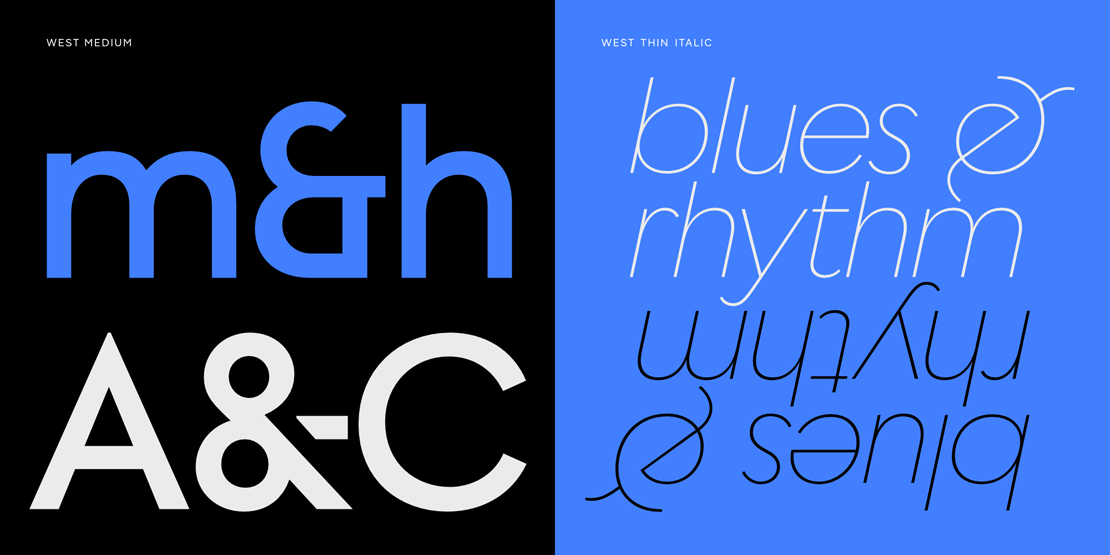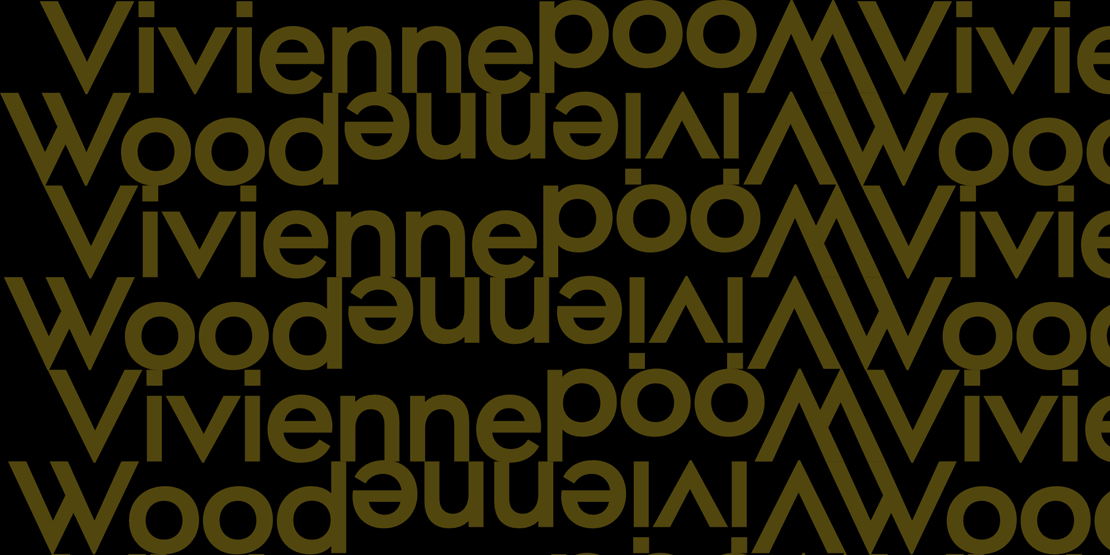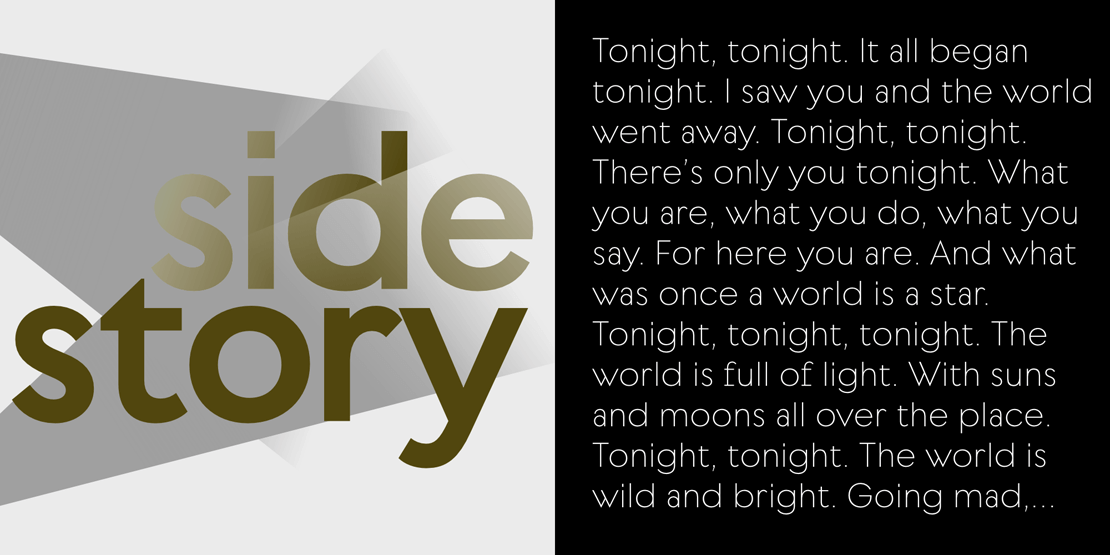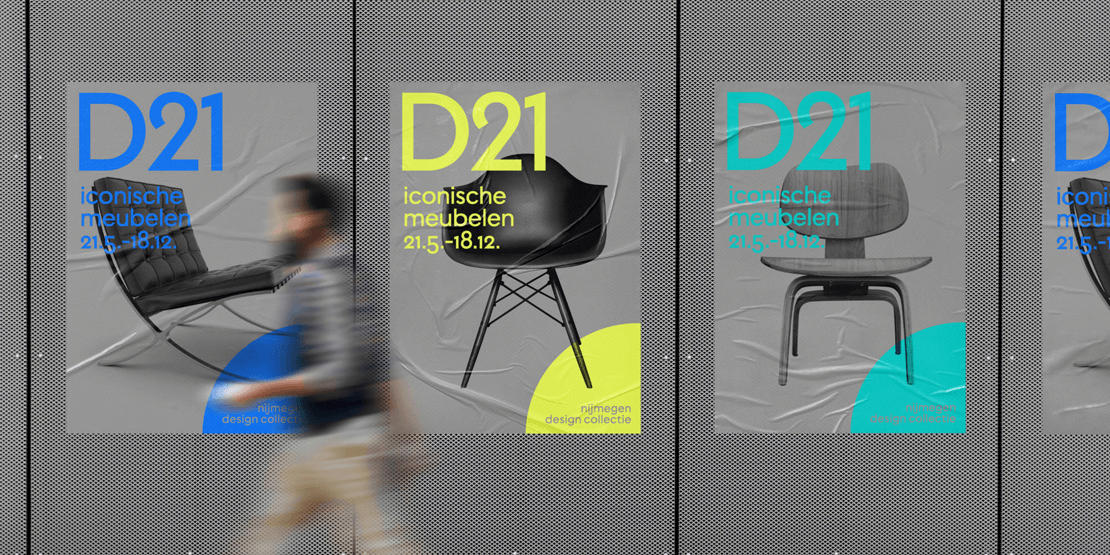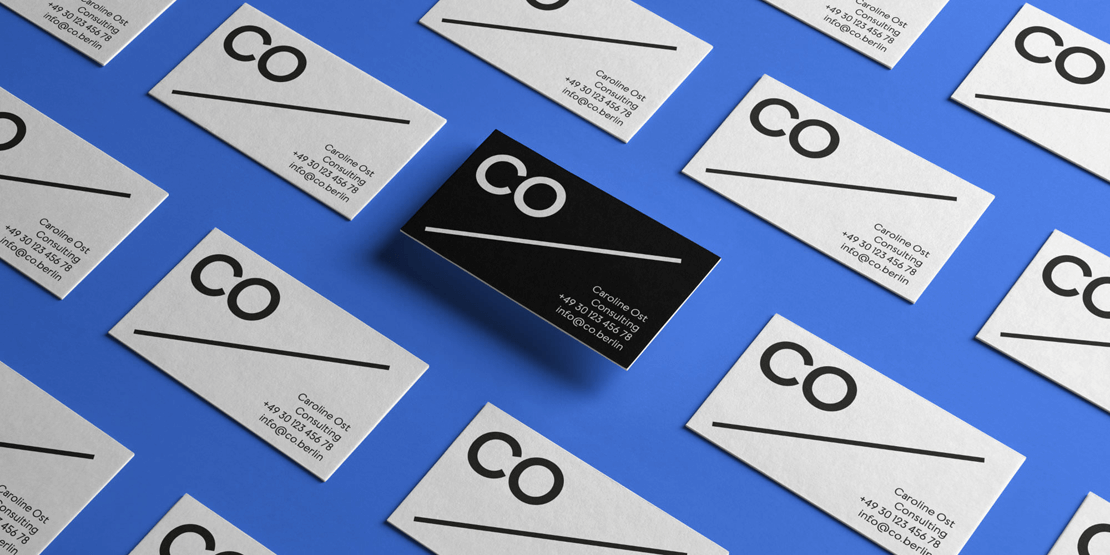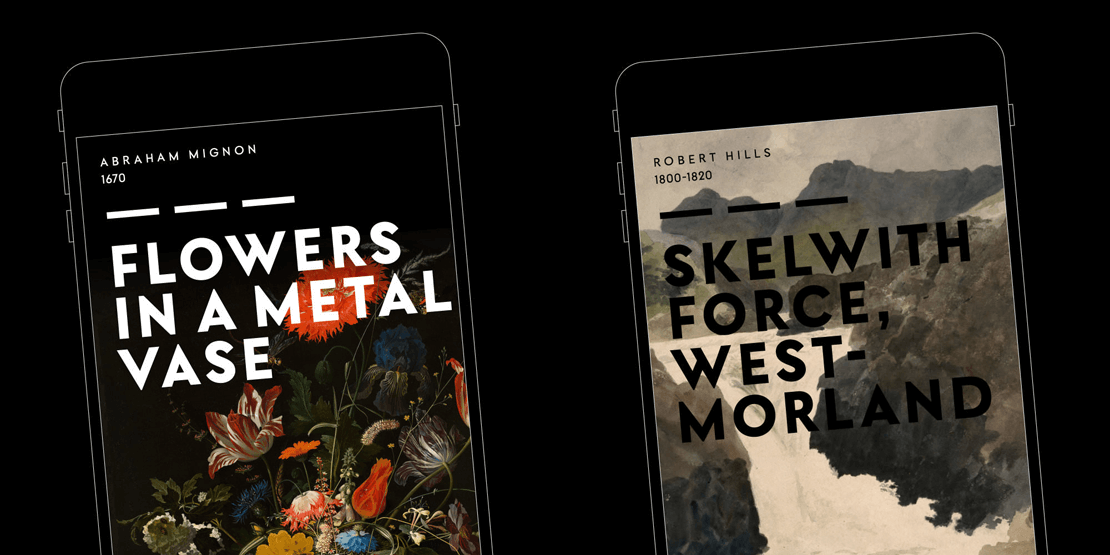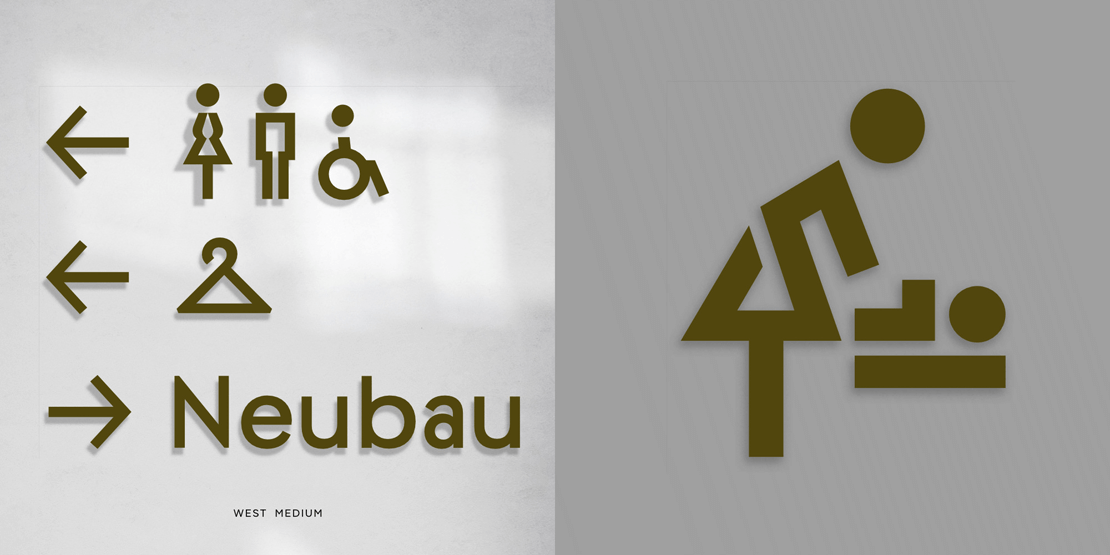
West: Geometrische Serifenlose mit eigenständigem Charakter
Daniel Perraudin interpretiert mit der »West« das Konzept der geometrischen Serifenlosen auf zeitgemäße und eigenständige Weise. Die Schriftfamilie ist neu bei Fontwerk erschienen.
»Optisch ähnliche Formen wiederholen sich nicht« lautet offiziell das Motto dieser Schriftart. Hinter der scheinbaren Leichtigkeit steckt jedoch eine Vielzahl unterschiedlicher Designentscheidungen ihres Gestalters Daniel Perraudin:
Um einen harmonischen Formenkanon zu bewahren und dem Konzept der Konstruktion und Symmetrie gerecht zu werden, variierte der Type-Designer zunächst einzelne Buchstabenbreiten (z.B. schmale a und s im Kontrast zu breiten b, n und J). Den hierdurch erzielten eigenständigen Charakter verstärkt er noch durch ungewöhnliche Glyphen wie W, t, f, 2, die Alternativformen des kursiven Q, die diagonalen Abschlüsse oder eckigen Punkte.
Dabei wechseln sich die Zeichen spielerisch zwischen Art-Deco-Einflüssen, monospacigen Einflüssen der Neunziger sowie der klassischen Wirkung maximal reduzierter geometrischer ab. Zusammen ergeben diese gestalterischen Eigenheiten eine ungewöhnliche und auffallende Mischung.
Neun Schriftschnitte von »Hairline« bis »Black«, kursive Schnitte und die im Komplettpaket enthaltenen Variable-Fonts sorgen für Flexibilität.
Durch die offene, eher unkompakte Zurichtung eignet sich die Schriftfamilie für den Displaybereich sowie für geringe Texte und Anwendungen bei Leit- und Orientierungssystemen gleichermaßen. Die Vorversion der Schrift wurde beispielsweise für das Leitsystem der Gemäldegalerie Alte Meister im Dresdner Zwinger verwendet. Für diese Zwecke wurden individuelle Wegfindungs-Symbole gestaltet, die in die vorliegenden Fonts übernommen und an die jeweilige Strichstärke angepasst wurden.